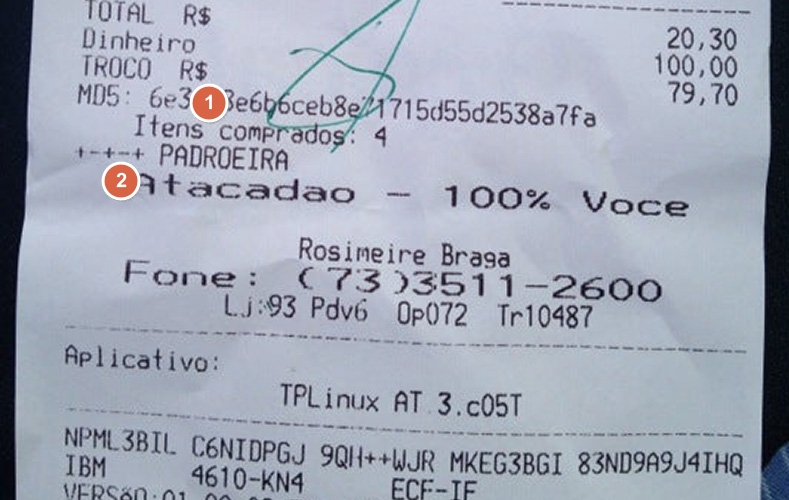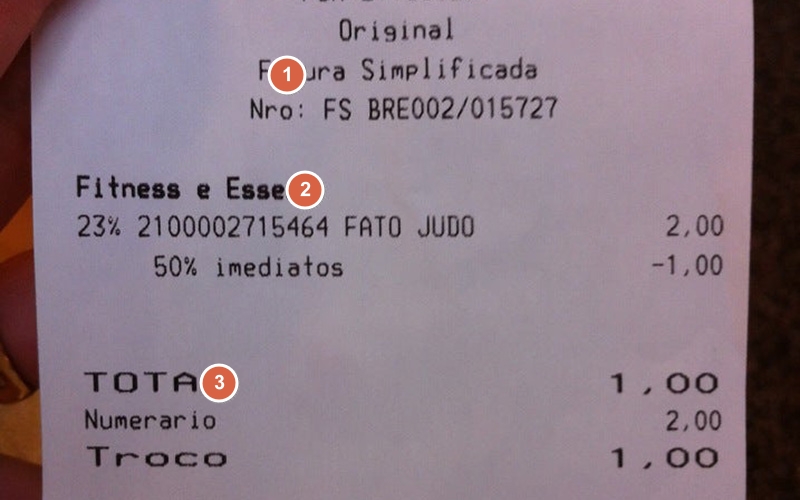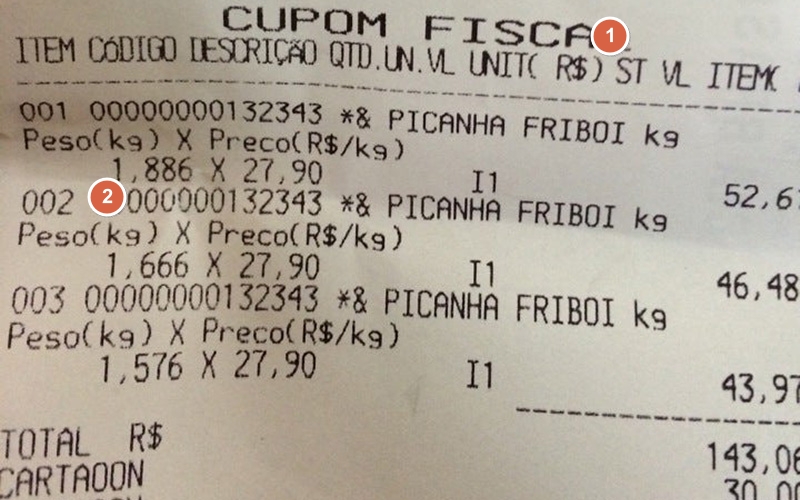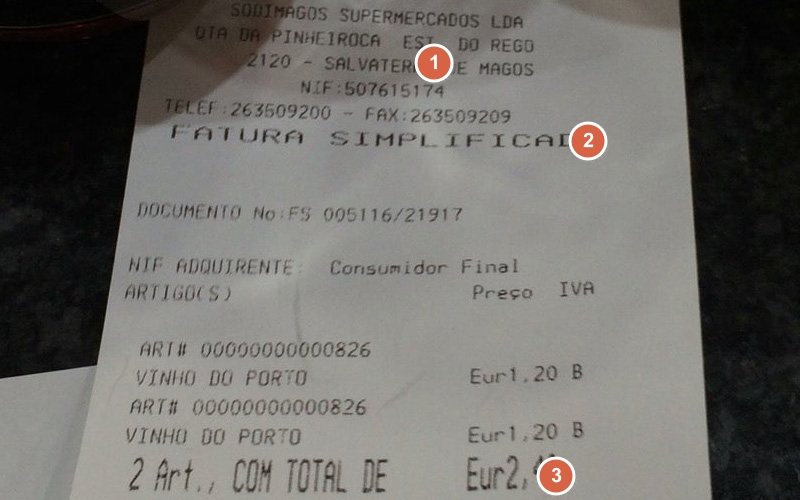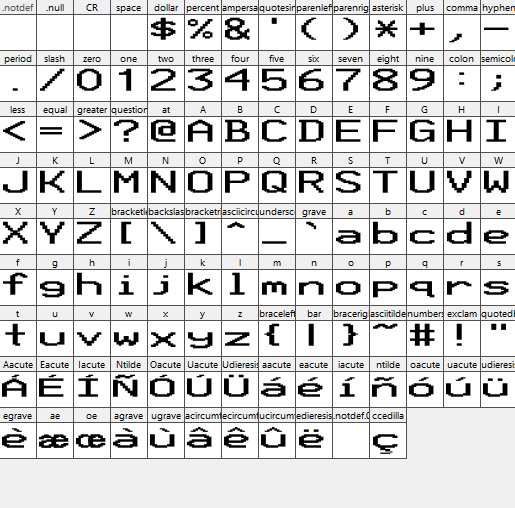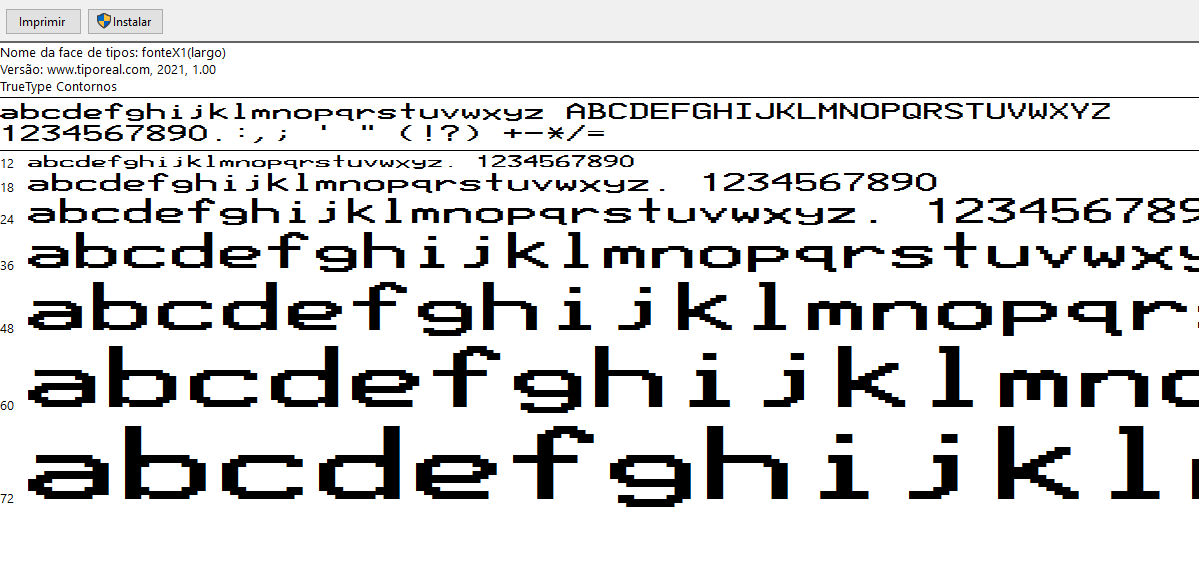
Amostra impressa da fonte para cupom fiscal de Atacadao em Brasil (❶fonteX1 ❷fonteX1-largo)⤴
Amostra impressa da fonte para fatura simplificada de um loja em Portugal (❶fonteX1 ❷fonteX1-negrito ❸fonteX1-largo )⤴
Amostra impressa da fonte para cupom fiscal de hipermercado Extra Hiper em Brasil (❶fonteX1-largo ❷fonteX1)⤴
Amostra impressa da fonte para fatura simplificada de um supermercado em Portugal (❶fonteX1 ❷fonteX1-largo ❸fonteX1-estreito)⤴
Todos os personagens⤴
O que parece quando aberto com o visualizador de fontes padrão do Windows⤴